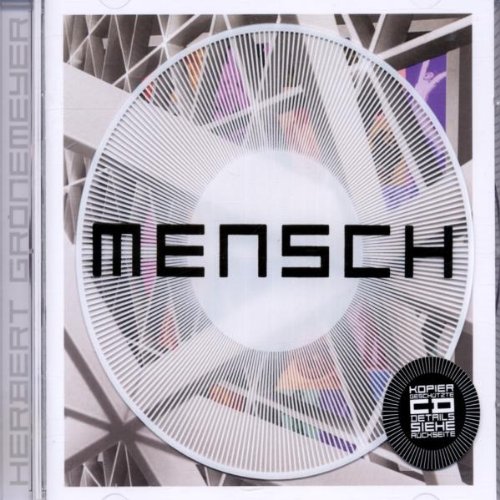
Ja, welche ist das..
Ich suche diese unfassbar schöne Schrift vom Grönemeyer Album Mensch.
Es wäre großartig, wenn mir da jemand behilflich sein könnte, ich weiß es leider nicht, und finde sie auch nicht.
es ist die Luggage. Das hat jetzt doch allein geklappt^^ Hat aber jemand zufällig eine Free Font, der so ähnlich ist?
also den kannst dir sicher in kürze selber bei fontstruct zusammenklicken, is ja „nur“ ein 5 x 5er raster.
Ich suche diese unfassbar schöne Schrift vom Grönemeyer Album Mensch.
Also, was ich bloß mal so daherfragen will … unfassbar schön … für die gezeigten Schriftzeichen: geht das wirklich in einem Atemzug/Aufwasch und zusammen? Schön allein ist ja schon mal was. So an sich und überhaupt. Aber unfassbar schön? Echt wahr und so?